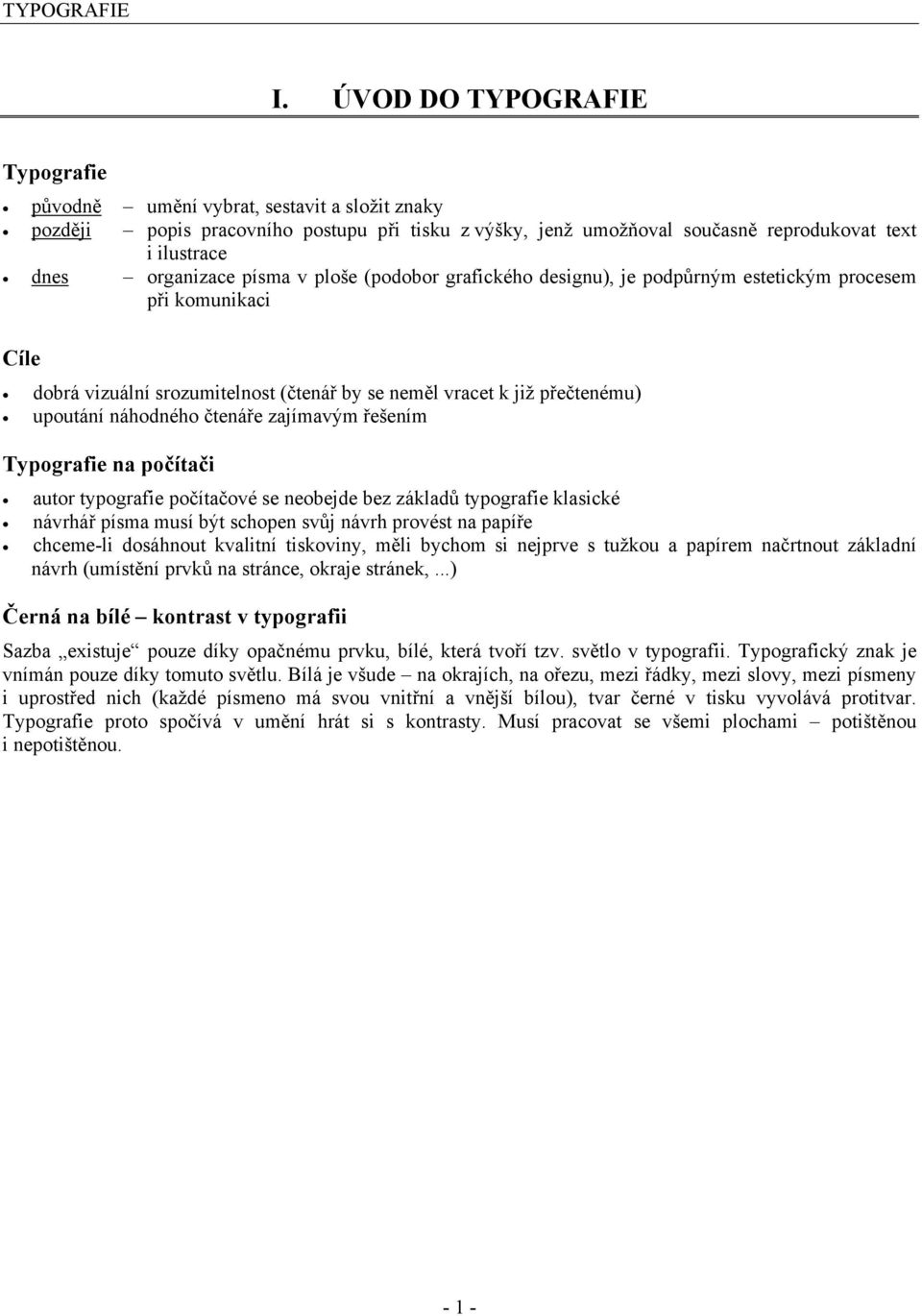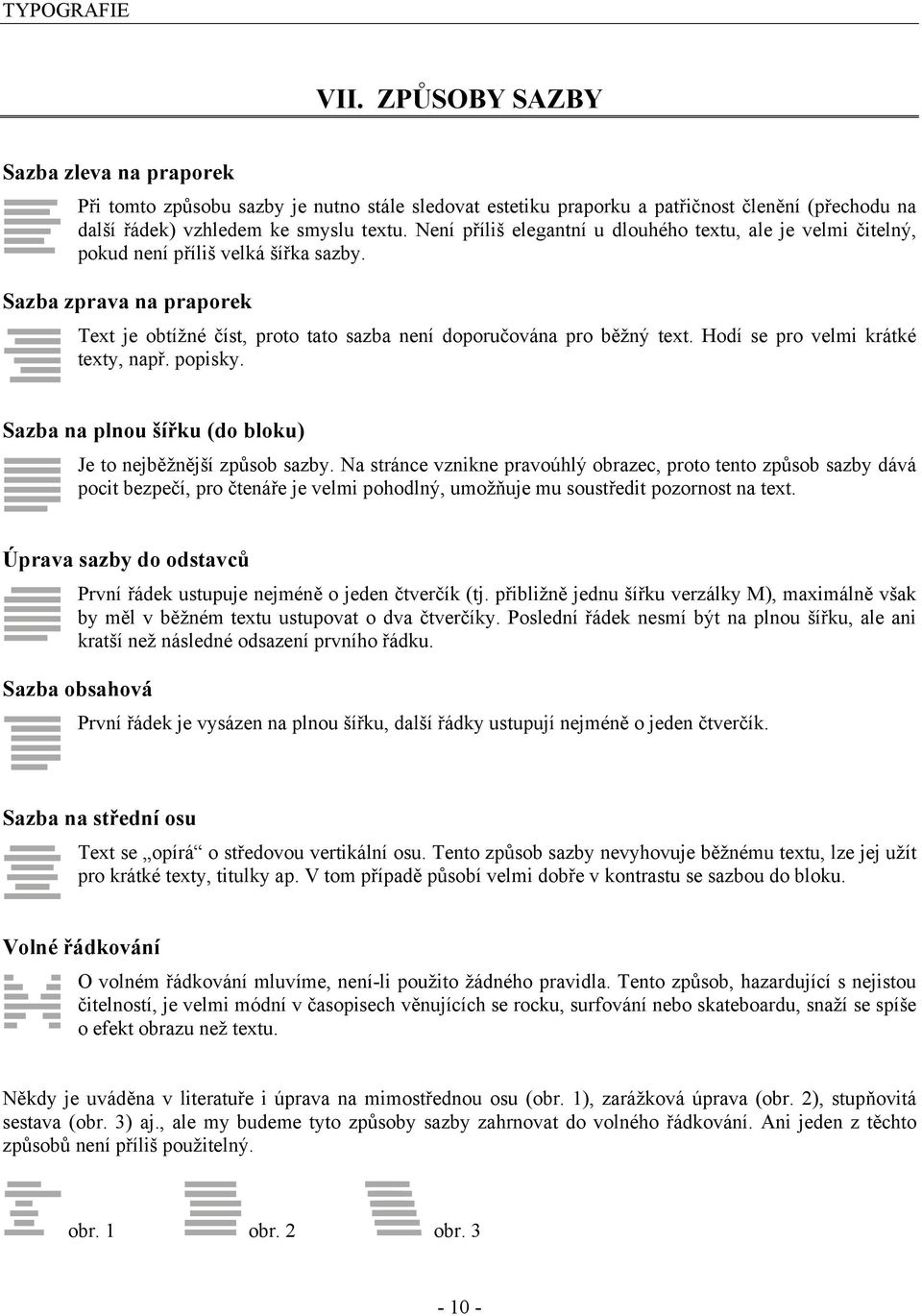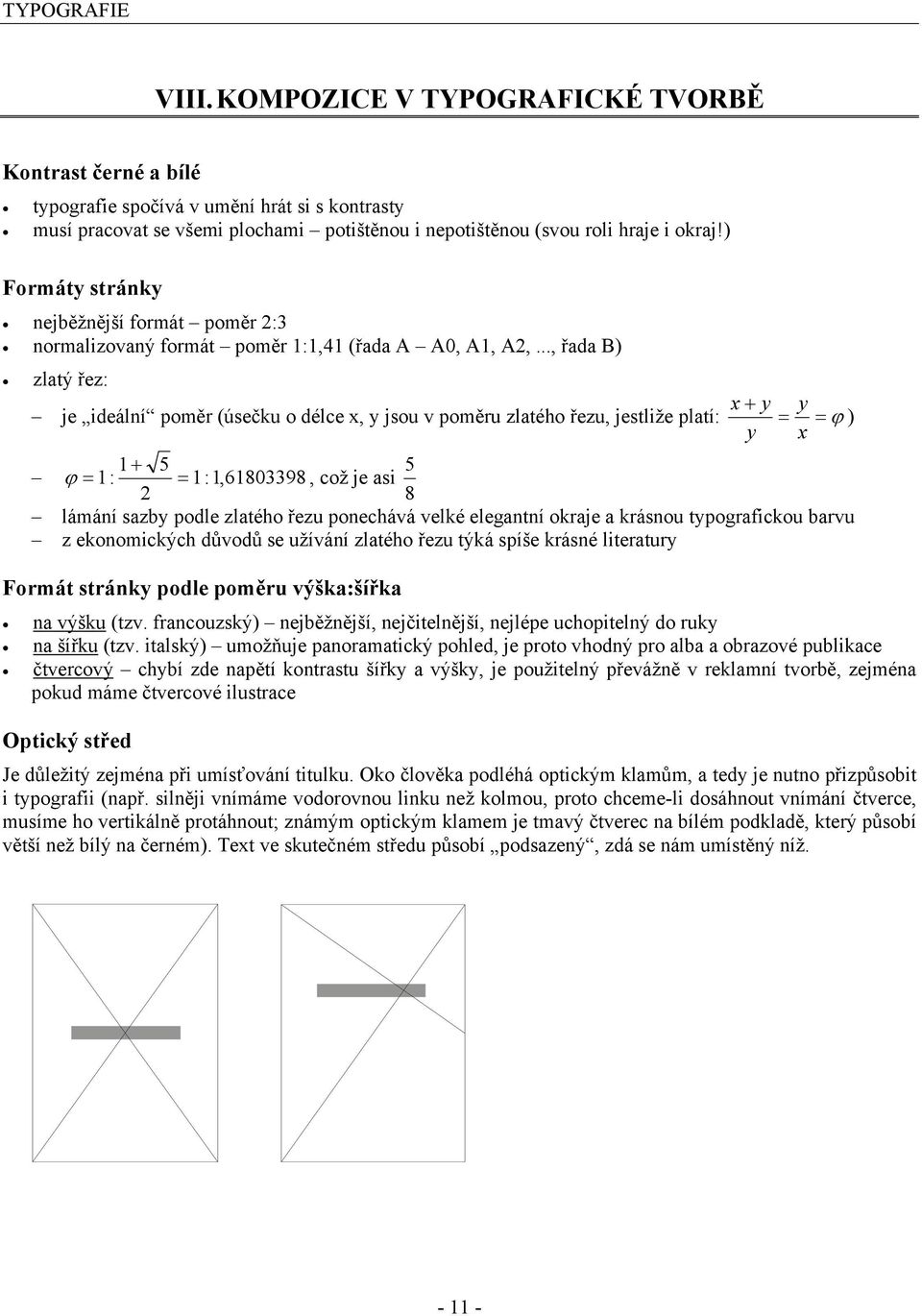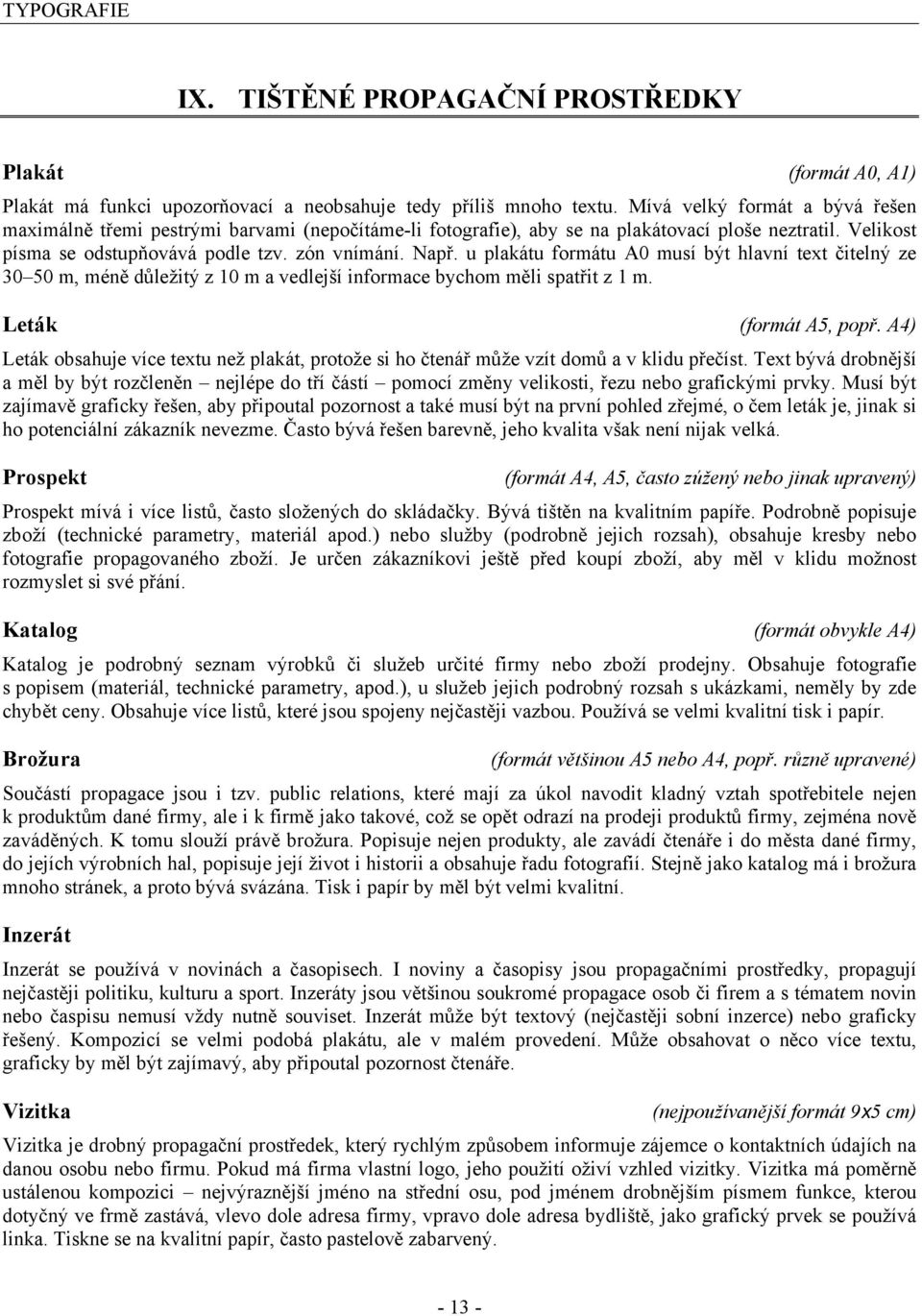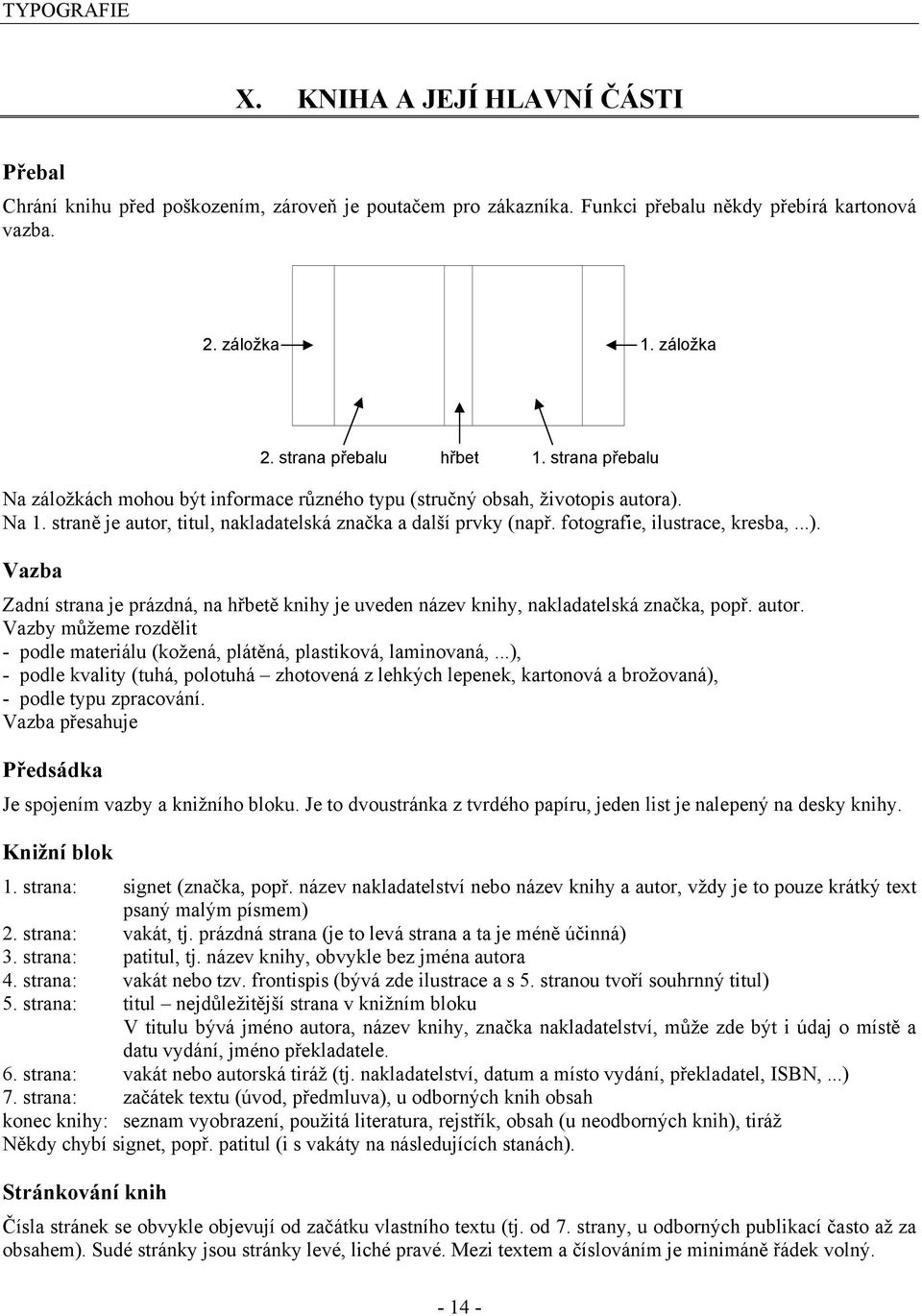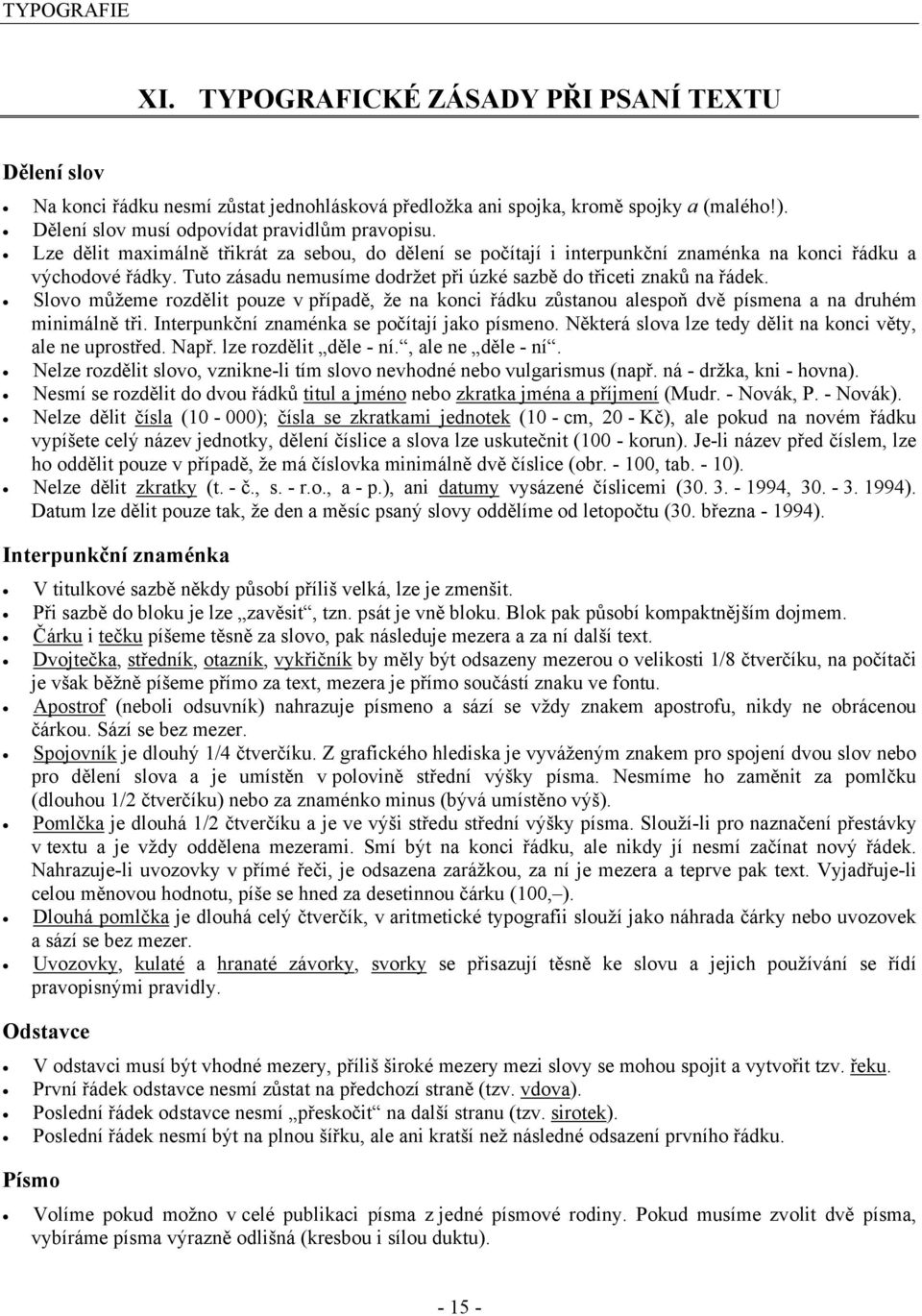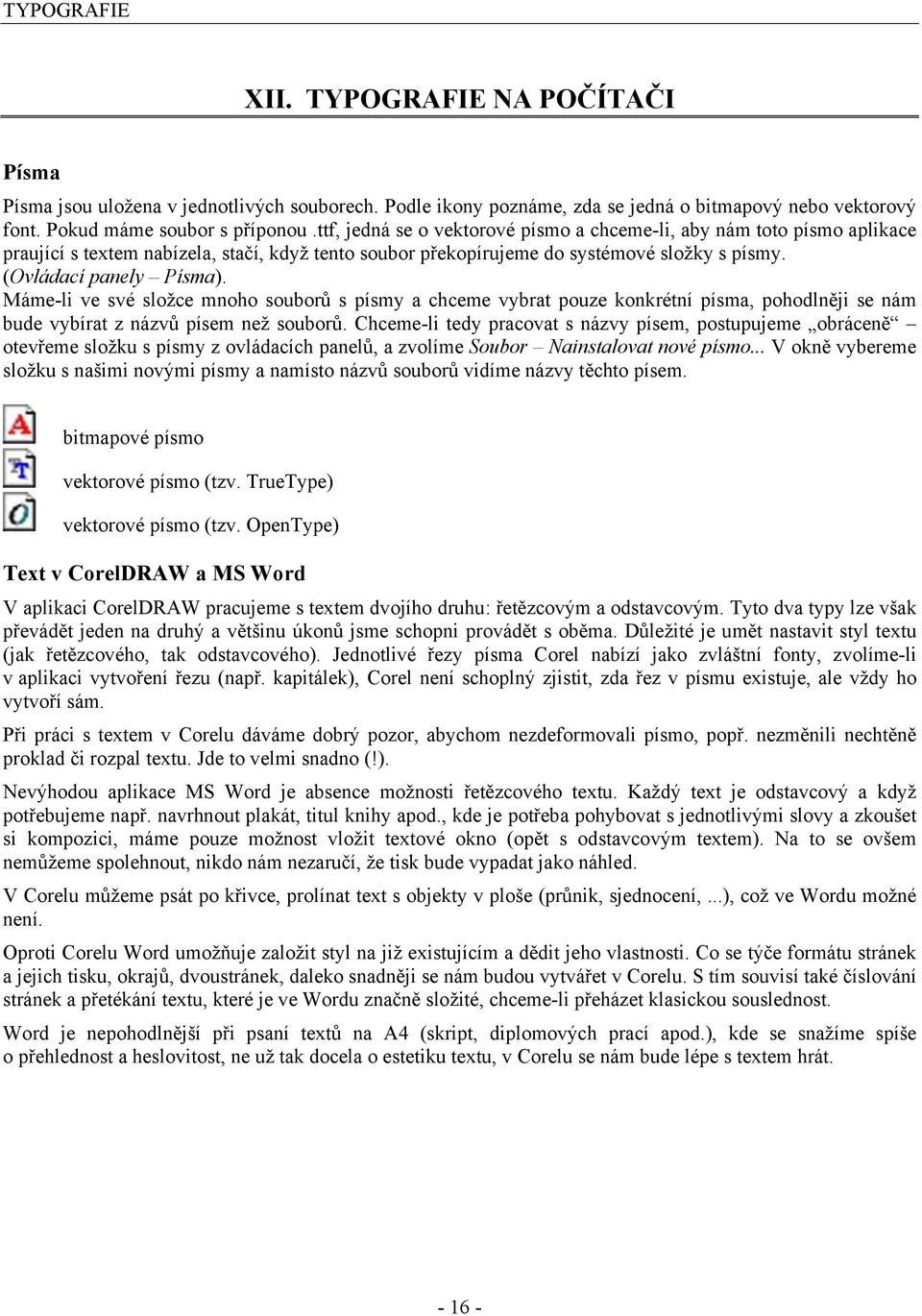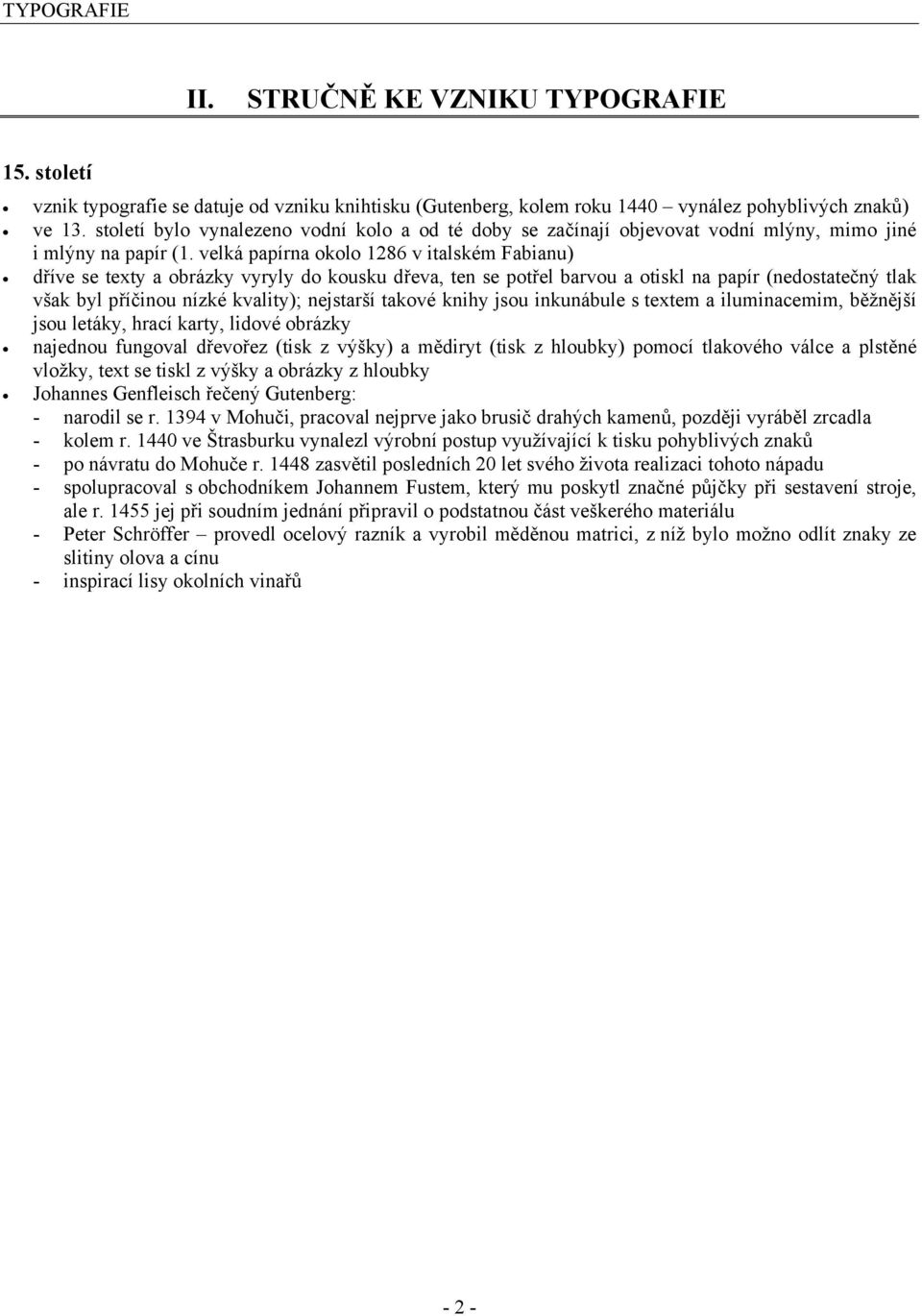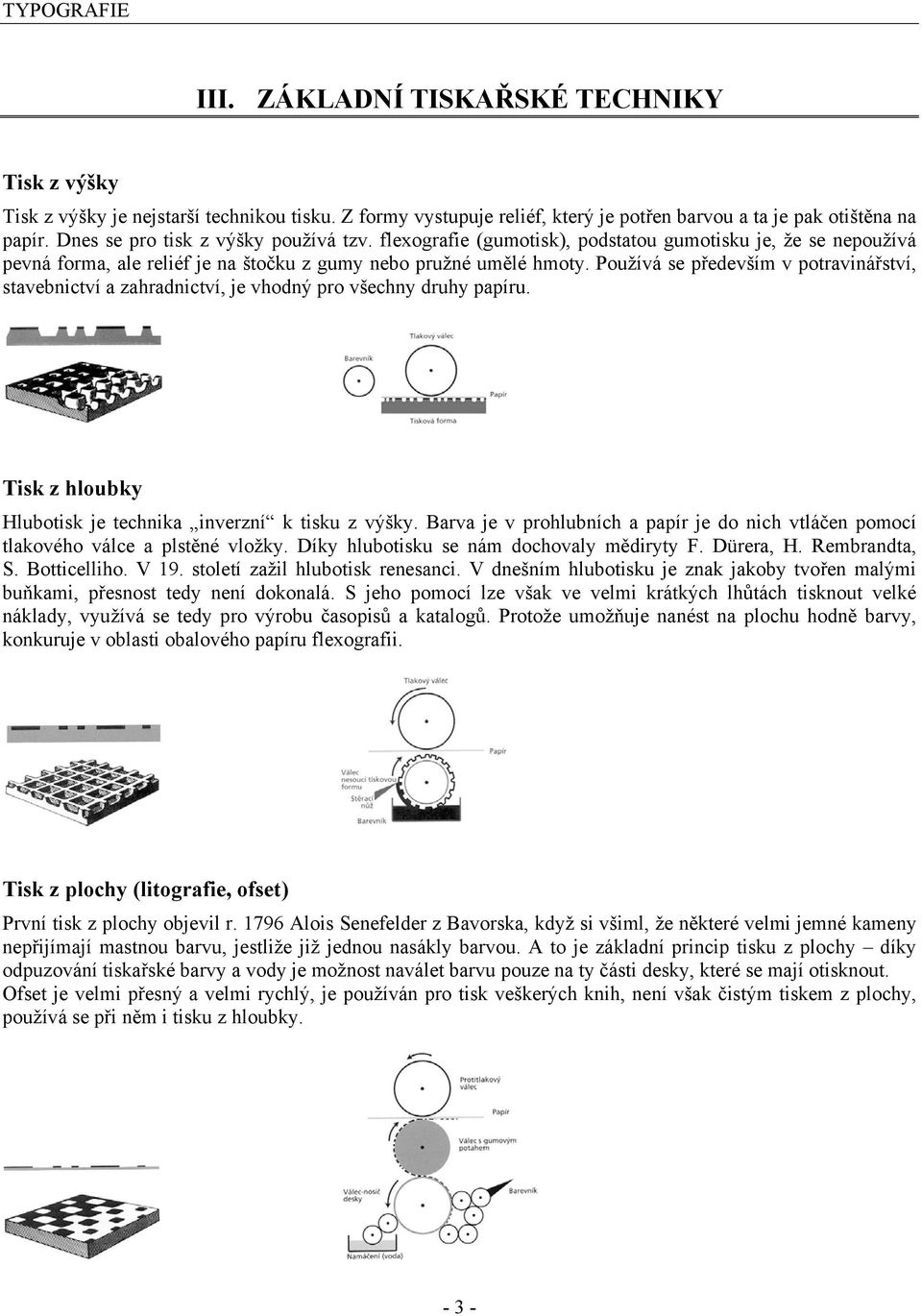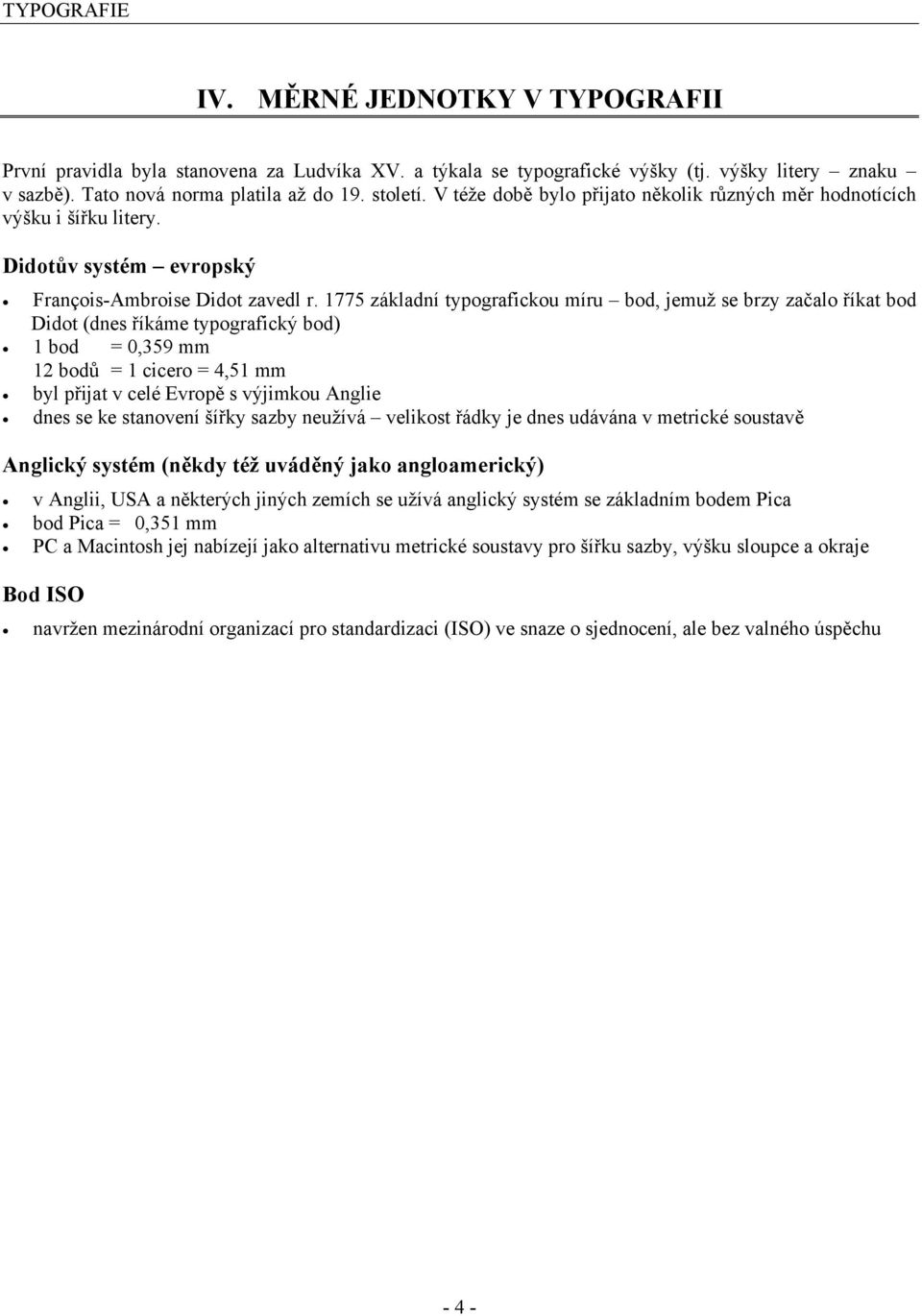
I. ÚVOD DO TYPOGRAFIE
- Karel Beránek
1 I. ÚVOD DO TYPOGRAFIE Typografie původně umění vybrat, sestavit a složit znaky později popis pracovního postupu při tisku z výšky, jenž umožňoval současně reprodukovat text i ilustrace dnes organizace písma v ploše (podobor grafického designu), je podpůrným estetickým procesem při komunikaci Cíle dobrá vizuální srozumitelnost (čtenář by se neměl vracet k již přečtenému) upoutání náhodného čtenáře zajímavým řešením Typografie na počítači autor typografie počítačové se neobejde bez základů typografie klasické návrhář písma musí být schopen svůj návrh provést na papíře chceme-li dosáhnout kvalitní tiskoviny, měli bychom si nejprve s tužkou a papírem načrtnout základní návrh (umístění prvků na stránce, okraje stránek,...) Černá na bílé kontrast v typografii Sazba existuje pouze díky opačnému prvku, bílé, která tvoří tzv. světlo v typografii. Typografický znak je vnímán pouze díky tomuto světlu. Bílá je všude na okrajích, na ořezu, mezi řádky, mezi slovy, mezi písmeny i uprostřed nich (každé písmeno má svou vnitřní a vnější bílou), tvar černé v tisku vyvolává protitvar. Typografie proto spočívá v umění hrát si s kontrasty. Musí pracovat se všemi plochami potištěnou i nepotištěnou
2 II. STRUČNĚ KE VZNIKU TYPOGRAFIE 15. století vznik typografie se datuje od vzniku knihtisku (Gutenberg, kolem roku 1440 vynález pohyblivých znaků) ve 13. století bylo vynalezeno vodní kolo a od té doby se začínají objevovat vodní mlýny, mimo jiné i mlýny na papír (1. velká papírna okolo 1286 v italském Fabianu) dříve se texty a obrázky vyryly do kousku dřeva, ten se potřel barvou a otiskl na papír (nedostatečný tlak však byl příčinou nízké kvality); nejstarší takové knihy jsou inkunábule s textem a iluminacemim, běžnější jsou letáky, hrací karty, lidové obrázky najednou fungoval dřevořez (tisk z výšky) a mědiryt (tisk z hloubky) pomocí tlakového válce a plstěné vložky, text se tiskl z výšky a obrázky z hloubky Johannes Genfleisch řečený Gutenberg: - narodil se r v Mohuči, pracoval nejprve jako brusič drahých kamenů, později vyráběl zrcadla - kolem r ve Štrasburku vynalezl výrobní postup využívající k tisku pohyblivých znaků - po návratu do Mohuče r zasvětil posledních 20 let svého života realizaci tohoto nápadu - spolupracoval s obchodníkem Johannem Fustem, který mu poskytl značné půjčky při sestavení stroje, ale r jej při soudním jednání připravil o podstatnou část veškerého materiálu - Peter Schröffer provedl ocelový razník a vyrobil měděnou matrici, z níž bylo možno odlít znaky ze slitiny olova a cínu - inspirací lisy okolních vinařů - 2 -
3 III. ZÁKLADNÍ TISKAŘSKÉ TECHNIKY Tisk z výšky je nejstarší technikou tisku. Z formy vystupuje reliéf, který je potřen barvou a ta je pak otištěna na papír. Dnes se pro tisk z výšky používá tzv. flexografie (gumotisk), podstatou gumotisku je, že se nepoužívá pevná forma, ale reliéf je na štočku z gumy nebo pružné umělé hmoty. Používá se především v potravinářství, stavebnictví a zahradnictví, je vhodný pro všechny druhy papíru. Tisk z hloubky Hlubotisk je technika inverzní k tisku z výšky. Barva je v prohlubních a papír je do nich vtláčen pomocí tlakového válce a plstěné vložky. Díky hlubotisku se nám dochovaly mědiryty F. Dürera, H. Rembrandta, S. Botticelliho. V 19. století zažil hlubotisk renesanci. V dnešním hlubotisku je znak jakoby tvořen malými buňkami, přesnost tedy není dokonalá. S jeho pomocí lze však ve velmi krátkých lhůtách tisknout velké náklady, využívá se tedy pro výrobu časopisů a katalogů. Protože umožňuje nanést na plochu hodně barvy, konkuruje v oblasti obalového papíru flexografii. Tisk z plochy (litografie, ofset) První tisk z plochy objevil r Alois Senefelder z Bavorska, když si všiml, že některé velmi jemné kameny nepřijímají mastnou barvu, jestliže již jednou nasákly barvou. A to je základní princip tisku z plochy díky odpuzování tiskařské barvy a vody je možnost naválet barvu pouze na ty části desky, které se mají otisknout. Ofset je velmi přesný a velmi rychlý, je používán pro tisk veškerých knih, není však čistým tiskem z plochy, používá se při něm i tisku z hloubky
4 IV. MĚRNÉ JEDNOTKY V TYPOGRAFII První pravidla byla stanovena za Ludvíka XV. a týkala se typografické výšky (tj. výšky litery znaku v sazbě). Tato nová norma platila až do 19. století. V téže době bylo přijato několik různých měr hodnotících výšku i šířku litery. Didotův systém evropský François-Ambroise Didot zavedl r základní typografickou míru bod, jemuž se brzy začalo říkat bod Didot (dnes říkáme typografický bod) 1 bod = 0,359 mm 12 bodů = 1 cicero = 4,51 mm byl přijat v celé Evropě s výjimkou Anglie dnes se ke stanovení šířky sazby neužívá velikost řádky je dnes udávána v metrické soustavě Anglický systém (někdy též uváděný jako angloamerický) v Anglii, USA a některých jiných zemích se užívá anglický systém se základním bodem Pica bod Pica = 0,351 mm PC a Macintosh jej nabízejí jako alternativu metrické soustavy pro šířku sazby, výšku sloupce a okraje Bod ISO navržen mezinárodní organizací pro standardizaci (ISO) ve snaze o sjednocení, ale bez valného úspěchu - 4 -
5 V. PÍSMO Stále musíme mít na paměti, že cílem je snadná četba, tj. dobrá vizuální srozumitelnost. Čtenář by se neměl vracet k již přečtenému, aby si ověřil, že četl správně (v knize vlastně musí typografie zůstat neviditelná, čtenář si nesmí při četbě uvědomovat znaky). Zároveň nesmíme čtenáři unavovat zrak střídáním překážek, jako jsou verzálky, kurzíva, tučná a podtržená slova (vysvětlení pojmů viz níže). Základní typografickou složkou je znak. Pro pochopení typografie musíme nejprve znát anatomii jednotlivých písem, naučit se rozlišovat různá písma a podle toho je vhodně vybírat. Znak versus písmeno všechno kromě mezer znak znak nemusí být nutně písmeno, znakem je také mezera (často se opovrhuje sazebními programy, kt. signalizují počet písmen a ne znaků např. Word) Duktus Duktus je síla tahu písma (někdy též váha písma). V téže abecedě musí být stejná tučnost: linie znaku jsou stejně široké, ostatní prvky struktur nebo zdobnosti mají tutéž optickou hutnost. Duktus jednoho písmene může být stejný v celém tvaru nebo se může měnit. Písmo s různou sílou duktu nazýváme písmem stínovým (stínový tah). Duté písmo neboli konturové (resp. drátěné) má tah vykreslený konturami (obrysem), přičemž vnitřek tahu zůstává nevyplněný. písmo stínové písmo nestínové Tučnost A jsme opět u kontrastu. Změnit tučnost znaku znamená pozměnit světlo, a tedy i změnit kontrast. Pomocí tučného písma můžeme mimořádně zdůraznit některé znaky, slova, řádky nebo odstavce. Příliš tučných slov v textu však znesnadňuje a zpomaluje čtení (viz některé učebnice zdůrazňující všechny důležité pojmy). Každý znak má nejméně tři tučnosti: může být slabý, polotučný a tučný. Běžně se setkáváme u písma s následující tučností: - velmi slabé (extra-light) - slabé (light) - normální (book nebo roman) - polotučné (medium) - tříčtvrtečně tučné (semi-bold) - tučné (bold) - velmi tučné (extra-bold) - ultratučné (ultra) - černé (black) - 5 -
6 Antikva versus kurzíva Antikva je vyvážený, přísně vertikální znak, kurzíva je potom znak skloněný doprava o Antikva má mnohem pevnější vzhled než kurzíva, nemusí být však nutně čitelnější. Je ovšem nutno dbát, aby se antikva s kurzívou příliš nestřídaly, rychlé střídání může být únavné (a neestetické). Kurzíva má za úkol rozlišovat prvky běžného textu, označuje zvláštní smysl nebo použití: - cizí slova a výrazy (a priori, alter ego,...) - tituly děl (Verdiho Requiem) - ve větách slova, písmena, výrazy, citovaná hesla (být redaktorem v Mondu, v referendu zaznělo ne, nevyslovuje se s, str. 18: číst úterý místo středa) - odkazy na poznámky, rejstřík (Hřib: viz Houby) - scénické poznámky v divadelních hrách (FIGARO, se zatajeným dechem: Uvidíte... (Odchází). Opona. ) - notový zápis (nácvik noty c) Verzálky, minusky, kapitálky VERZÁLKY velká písmena V prvních stoletích existence písma byly používány pouze verzálky a kapitálky. Výborně se hodí na nápisy tesané do kamene. Dnes mají verzálky především signalizační význam (začátek věty, vlastní jméno apod.), podle toho bychom je měli také používat. MINUSKY malá písmena Minusky vznikaly dlouhým vývojem jako technická nutnost. Bylo potřeba šířit vzdělání pomocí knih, ale pro rychlé opisování textů se verzálky příliš nehodí. Psaní velkých a malých písmen je nutno ovládat, protože mnohdy změní smysl celé věty (např. měsíc je část roku nebo libovolná oběžnice, Měsíc je oběžnice naší planety). Zároveň však neúměrné používání verzálek mate čtenáře, jejich užití by mělo mít vždy smysl. Čtenář zkrátka musí snadno pochopit autorovy záměry. KAPITÁLKY verzálky přibližně o výšce minusek V typografii se užívají v následujících případech: - u prvního slova (prvních slov) následjícího po iniciále - u podpisů článků, předmluv ap. - pro jména autorů v bibliografiích - pro titulky článků v právnických textech - pro jména osob a obsazení v divadelních hrách - pro římské číslice označující století Některé písmové řady nemají kapitálky. Sázecí programy sice umožňují psaní kapitálkami, ale ty jsou vytvářeny většinou pouze mírným zmenšením verzálek, což výrazně změní duktus písmene, slovo psané těmito kapitálkami se uprostřed textu propadá. Pokud tedy nemáme řadu obsahující kapitálky, zvolíme raději jiné písmo nebo se kapitálkám vyhneme. pravé kapitálky v písmu Bodoni vytvořené KAPITÁLKY pomocí aplikace Word vytvořené KAPITÁLKY změnou velikosti písma - 6 -
7 Písmová rodina, řezy písma Každý typ písma má svůj název a od jiného typu se liší svou kresbou. Je navrženo tzv. základní písmo a od něj se odvozují tzv. řezy. Tyto řezy zachovávají kresbu, od základního písma se liší sílou duktu (tučné, light), sklonem (kurzíva), šířkou, zvláštním řezem jsou i kapitálky. Výtvarník vždy navrhuje písmo základní i s jeho řezy. Písmo se všemi svými řezy nazýváme písmovou rodinou. V jedné publikaci bychom měli používat písma jedné písmové rodiny, pokud použijeme dvě, měla by obě písma být výrazně odlišná (kresbou i sílou duktu). Písmový font Definovat písmový font je velice obtížné, protože každá aplikace pracuje s písmy jiným způsobem. Jednotlivé řezy písma se totiž obvykle ukládají v počítači do zvláštních souborů a ne každý sázecí program je schopen rozpoznat celou písmovou rodinu. Takže font je vlastně písmo, které nám aplikace nabízí se všemi jeho velikostmi. Např. MS Word, Corel Draw, QuarkXPress nám nabízí každý řez písma zvlášť jako různé fonty, Adobe InDesign nabízí jako font základní písmo a řez nám umožní zvolit pouze v případě, že našel soubor s tímto řezem (tj. tato aplikace vlastní řezy z písma nevytváří). Bitmapový font má znak přesně definován v určité velikosti pomocí tisknoucích se a netisknoucích se bodů, musí obsahovat vzory písma pro tiskárnu, obrazovku, všechny řezy a jejich velikosti zvlášť. Pokud použijeme větší velikost písma než jakou font obsahuje, dojde ke zvětšení bodů, z nichž se písmo skládá. Místo bodu vznikne čtvereček a písmo je hrbolaté. Používají je různé aplikace, sázecí program nám je však většinou nenabízí. Vektorový font si pamatuje znaky pomocí analytického zápisu křivky písmene, proto zvětšení písmene nemá vliv na hladkost kresby. abcdefg vektorový font bitmapový font Písmová osnova Akcentová dotažnice Horní dotažnice (horní účaří) akcent Střední dotažnice Střední výška písma Základní dotažnice (spodní účaří) výška verzálky Dolní dotažnice - 7 -
8 Přetah Písmena obsahující oblé tahy (p, o, u, q,...) se těmito oblými tahy dotažnic nedotýkají, ale mírně dotažnici přesahují (kdyby tomu tak nebylo, písmena se nám budou zdát menší). Toto přesahování přes dotažnici nazýváme přetah. Stupeň písma Stupněm písma budeme rozumět vzdálenost dvou dolních dotažnic dvou následujících řádků. (V literatuře se používá i názvu kuželka, který však původně znamenal výšku litery v ručně sázeném textu.) Čtverčík je prostor rovnající se mezeře, kde šířka rovná se výšce daného stupně. Proporcionální, neproporcionální písmo Každý znak má svou šířku, např. m je určitě širší než i. Většina písem je proporcionální, tj. přizpůsobuje text šířce každého znaku. Písmo neproporcionální považuje všechny znaky za stejně široké, takže i doplní mezerou do šířky čtverčíku (např. Courier). Text psaný takovým písmem je velmi nerovnoměrně prosvětlen a působí velmi nevyrovnaně a nevzhledně. proporcionální písmo neproporcionální písmo Klasifikace písem Klasifikací písem je celá řada, my si uvedeme pouze základní rozlišení typů písem. SERIFOVÁ PÍSMA patková Znaky jsou zakončeny tzv. patkami (např. Times New Roman). BEZSERIFOVÁ PÍSMA bezpatková Bezserifová písma nemají patky na konci tahů (např. Arial). PSANÁ PÍSMA Psaná písma jsou napodobením rukopisu. Jako jediná nemusejí mít mezeru mezi jednotlivými znaky ve slově. LOMENÁ PÍSMA Lomená písma jsou písma napodobující písma gotická
9 VI. ÚPRAVA SVĚTLOSTI TEXTU Text na stránce na nás působí jako šedá plocha. Tato šeď by měla být rovnoměrná, zároveň (hlavně) však světlost textu upravujeme z důvodu lepší čitelnosti textu. Např. mezery mezi písmeny nemohou být příliš velké, abychom rozeznali slova, ale ani příliš malé, aby nám jednotlivá písmena nesplývala. V každé aplikaci pro práci s textem lze pracovat jak s mezerami uvnitř slova, tak mezislovními mezerami, i s tzv. prokladem sazby. Prostrkávání (rozpal) Je to úprava mezer mezi písmeny. Sázecí programy mají uloženu tabulku tzv. párových mezer (mezi každými dvěma znaky), popř. tzv. skupinových mezer (mezi více znaky). Párové mezery stanovuje už návrhář písma. Teoreticky by měla být tato tabulka dokonalá, ale někdy potřebujeme rozpal upravit ručně, což umožňuje přímo aplikace. Velice stručně řečeno, obsah bílé plošky mezi dvěma písmeny by měl být konstantní. Nulová může být tato mezera pouze v případě, že se písmena nemohou dotknout (např. AV). Výjimku tvoří písma psaná, protože ta mají za úkol napodobovat psaný text, v němž písmena na sebe navazují. Mezery mezi slovy mezislovní mezera má velikost 1/3 čtverčíku před interpunkčními znaménky se nachází osminová mezera (: ;?!) zúžená mezera má hodnotu 1/4 nebo 1/5 čtverčíku nedá-li se oddělit při užití mezery jeden znak od druhého, hovoříme o nedělitelné (pevné) mezeře (Použití jednotlivých typů mezer viz kapitola Typografické zásady při psaní dlouhého textu.) Pokud sázíme text do bloku (viz kapitola Způsoby sazby), musíme dávat stále pozor na příliš velké mezery v textu (použijeme dělení slov, změníme slovosled, přidáme slovo). Kromě estetických důvodů tyto přílišné mezery zhoršují čitelnost, na více řádcích se mohou spojit a vytvořit světlé plochy (tzv. řeky). Proklad sazby (řádkování), šířka sazby Sloupec se skládá ze stejně dlouhých řádek, které jsou od sebe odděleny daným prokladem. Aby byla zachována dobrá čitelnost písma se stupněm bodů, doporučuje se nepřekročit asi 65 znaků v řádku, přílliš velká šířka sazby znesnadňuje čtení při přechodu na další řádek. Např. v tisku se z tohoto důvodu běžně užívá sloupců. Proklad je v počítači stanoven podle písma, lze jej však v aplikaci měnit. Pro text se stupněm 9 by proklad měl být bodů, se stupněm 12 by měl být bodů. Pokud titulek zabírá více řádek, je vhodné zmenšit jeho proklad, neboť vzniklá plocha je opticky příliš velká. Slabý proklad je však možné použít v běžném textu pouze mezi krátkými řádky
10 VII. ZPŮSOBY SAZBY Sazba zleva na praporek Při tomto způsobu sazby je nutno stále sledovat estetiku praporku a patřičnost členění (přechodu na další řádek) vzhledem ke smyslu textu. Není příliš elegantní u dlouhého textu, ale je velmi čitelný, pokud není příliš velká šířka sazby. Sazba zprava na praporek Text je obtížné číst, proto tato sazba není doporučována pro běžný text. Hodí se pro velmi krátké texty, např. popisky. Sazba na plnou šířku (do bloku) Je to nejběžnější způsob sazby. Na stránce vznikne pravoúhlý obrazec, proto tento způsob sazby dává pocit bezpečí, pro čtenáře je velmi pohodlný, umožňuje mu soustředit pozornost na text. Úprava sazby do odstavců První řádek ustupuje nejméně o jeden čtverčík (tj. přibližně jednu šířku verzálky M), maximálně však by měl v běžném textu ustupovat o dva čtverčíky. Poslední řádek nesmí být na plnou šířku, ale ani kratší než následné odsazení prvního řádku. Sazba obsahová První řádek je vysázen na plnou šířku, další řádky ustupují nejméně o jeden čtverčík. Sazba na střední osu Text se opírá o středovou vertikální osu. Tento způsob sazby nevyhovuje běžnému textu, lze jej užít pro krátké texty, titulky ap. V tom případě působí velmi dobře v kontrastu se sazbou do bloku. Volné řádkování O volném řádkování mluvíme, není-li použito žádného pravidla. Tento způsob, hazardující s nejistou čitelností, je velmi módní v časopisech věnujících se rocku, surfování nebo skateboardu, snaží se spíše o efekt obrazu než textu. Někdy je uváděna v literatuře i úprava na mimostřednou osu (obr. 1), zarážková úprava (obr. 2), stupňovitá sestava (obr. 3) aj., ale my budeme tyto způsoby sazby zahrnovat do volného řádkování. Ani jeden z těchto způsobů není příliš použitelný. obr. 1 obr. 2 obr